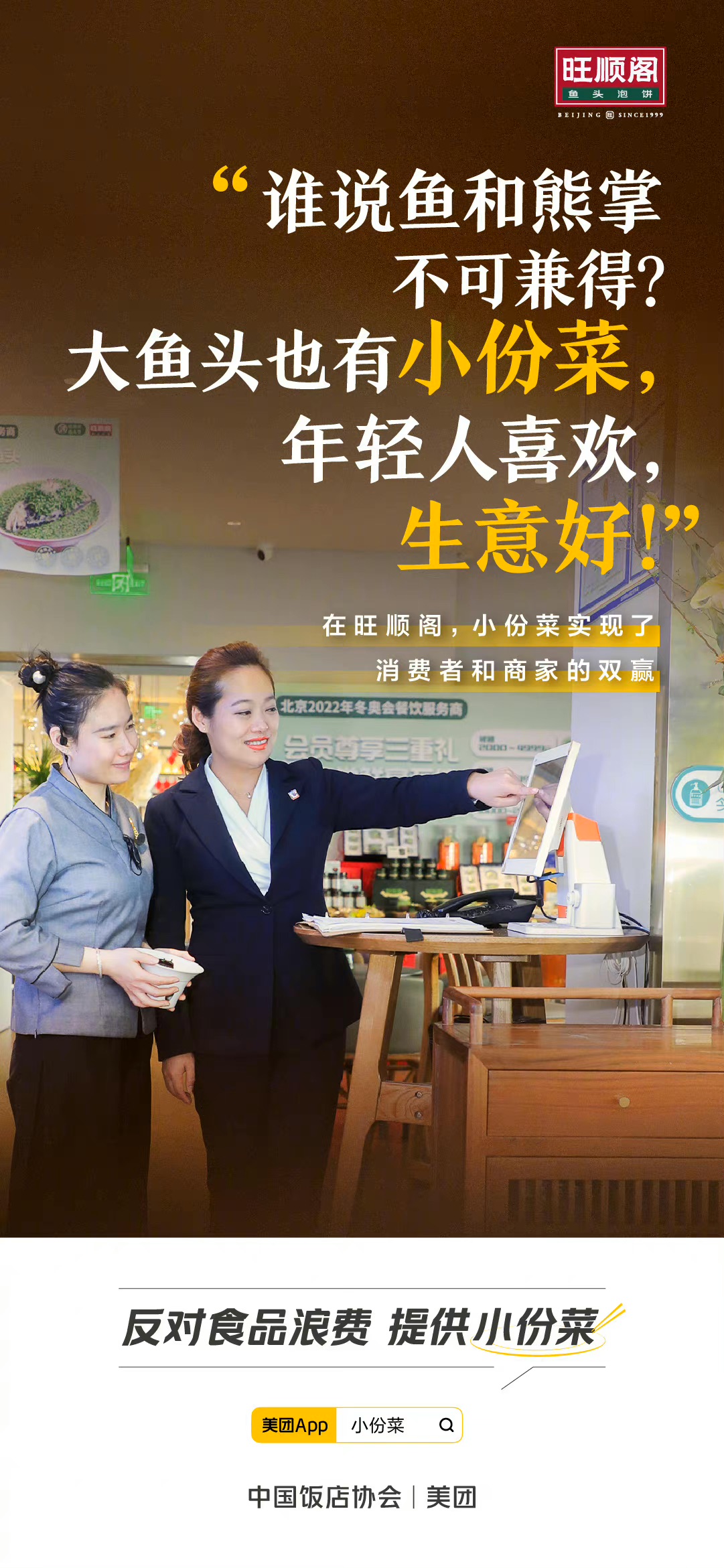
方正显仁体
崔显仁
宋体、创意字体
方正显仁体是由街头残疾艺人崔显仁先生创作。这款字体带有宋体风格,字形扁方,横细竖粗,横笔画的起笔处微微上翘,竖和撇笔画的起笔处往下凹陷,折笔处带有饰线,竖钩的造型特异,转折尤为突出。其风格隽秀大方,古香古色,适用于传统古典类的广告和产品包装设计。这款字体的全部收益都归崔显仁所有,这不仅是对他的特别关爱,更是对他身残志坚的敬意。